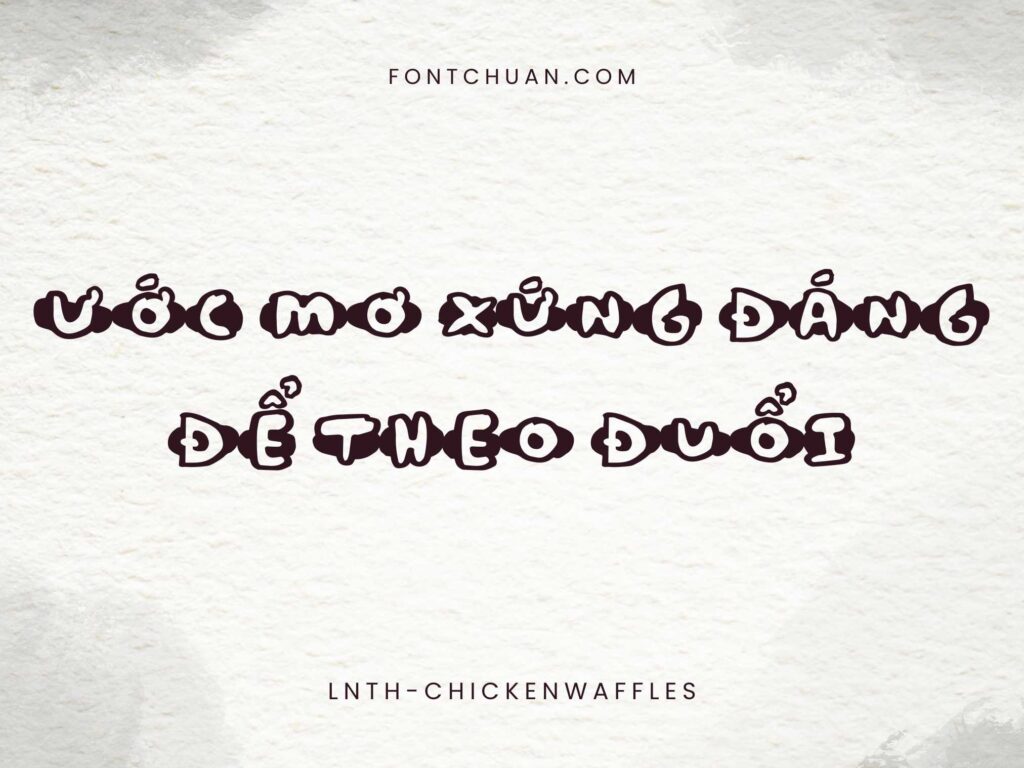
Font LNTH Chicken Waffles Việt Hóa
Tác giả Font: Xerographer Fonts
Chicken Waffles là một phông chữ viết tay độc đáo, mang phong cách vui tươi và thân thiện. Phông chữ này được thiết kế với những đường nét mềm mại và ngẫu hứng, tạo nên sự gần gũi và ấm áp cho các thiết kế. Với đặc trưng sinh động và tinh thần lễ hội, Chicken Waffles cũng có thể được xem là một Font chữ Halloween, phù hợp cho các dự án cần không khí vui nhộn, sáng tạo và phá cách. Bản Việt hóa do LNTH thực hiện giúp phông chữ này hỗ trợ đầy đủ các ký tự tiếng Việt, giúp người dùng dễ dàng áp dụng trong các dự án đa ngôn ngữ. Phông chữ này đã được sưu tầm và đăng tải bởi thành viên của Font Chuẩn nhằm đáp ứng nhu cầu đa dạng của cộng đồng thiết kế.
Về đặc điểm thiết kế, Chicken Waffles sở hữu các ký tự được vẽ tỉ mỉ, mang lại cảm giác tự nhiên và phóng khoáng. Phông chữ này đặc biệt phù hợp cho các dự án như thiệp mời, bìa sách, poster, logo và các ấn phẩm quảng cáo, nơi cần sự sáng tạo và ấn tượng mạnh mẽ. Ngoài ra, Chicken Waffles cũng thích hợp cho các sự kiện như lễ hội, sinh nhật, Halloween và Trung thu, mang lại không khí vui tươi và sôi động. Trong lĩnh vực ngành nghề, phông chữ này được ứng dụng rộng rãi trong quảng cáo, thiết kế thiệp cưới, giáo dục và công nghệ, góp phần tạo nên sự độc đáo và thu hút cho các sản phẩm và thương hiệu.